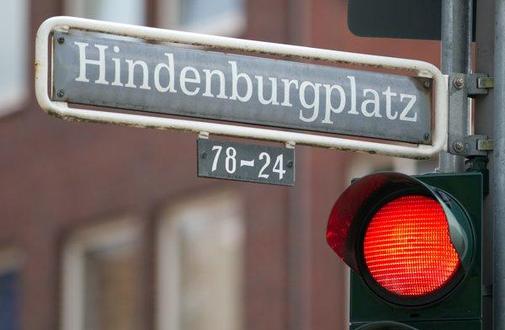
Münster Straßenschilder-Schrift
Weiss jemand, welche Schriftart in Muenster fuer Strassenschilder benuetzt wird?
Jaa genau so ein Schild meinte ich. Habs vorhin mal auf "what the font" ausprobiert und da kam "Weidemann Medium" bei raus.. aber Egyptian 505 koennte es auch sein!
Die hier sieht aus wie die Egyptian 505
Die Egyptienne 505 ist IIRC ein Nachbau der ATF-Antique von Barnhardth Bros. & Spindler type foundry (1842). Die wurde dann 1905 neu und überarbeitet unter den Namen Antique 1 veröffentlicht und damit recht beliebt. Die gab es mal eine Weile bei http://www.fontsite.com zum freien Herunterladen. Leider ist sie dort verschwunden und man kann sie nur noch über Dritte beziehen:
Jaa genau so ein Schild meinte ich. Habs vorhin mal auf "what the font" ausprobiert und da kam "Weidemann Medium" bei raus.. aber Egyptian 505 koennte es auch sein!
Dann hast du nicht bedacht, die perspektivische Verzerrung zu korrigieren. Die Weidemann kann es allein schon wegen des "g" und wegen der Breite nicht sein …
Zur Geschichte (und ihrer Namensgebung) der Egyptian 505 sagt MyFonts was anderes:
»This face was designed by Andre Guertler’s class in room 505 at the Kuenstgewerbeschule in Basel. It follows the principles of Frutiger’s Egyptienne, and won the first of the VGC type competitions.«
Zur Geschichte (und ihrer Namensgebung) der Egyptian 505 sagt MyFonts was anderes:
Ja. Das ist ein Widerspruch zu den Informationen die ich so habe. Demnach wäre die Egyptienne 505 eine unabhängige Entwicklung. Trotzdem sehen sich beide Schriften viel zu ähnlich? Die Egyptienne 505 läuft so ziemlich überall als Äquivalent zur (ATF) Antique 1 von 1905.